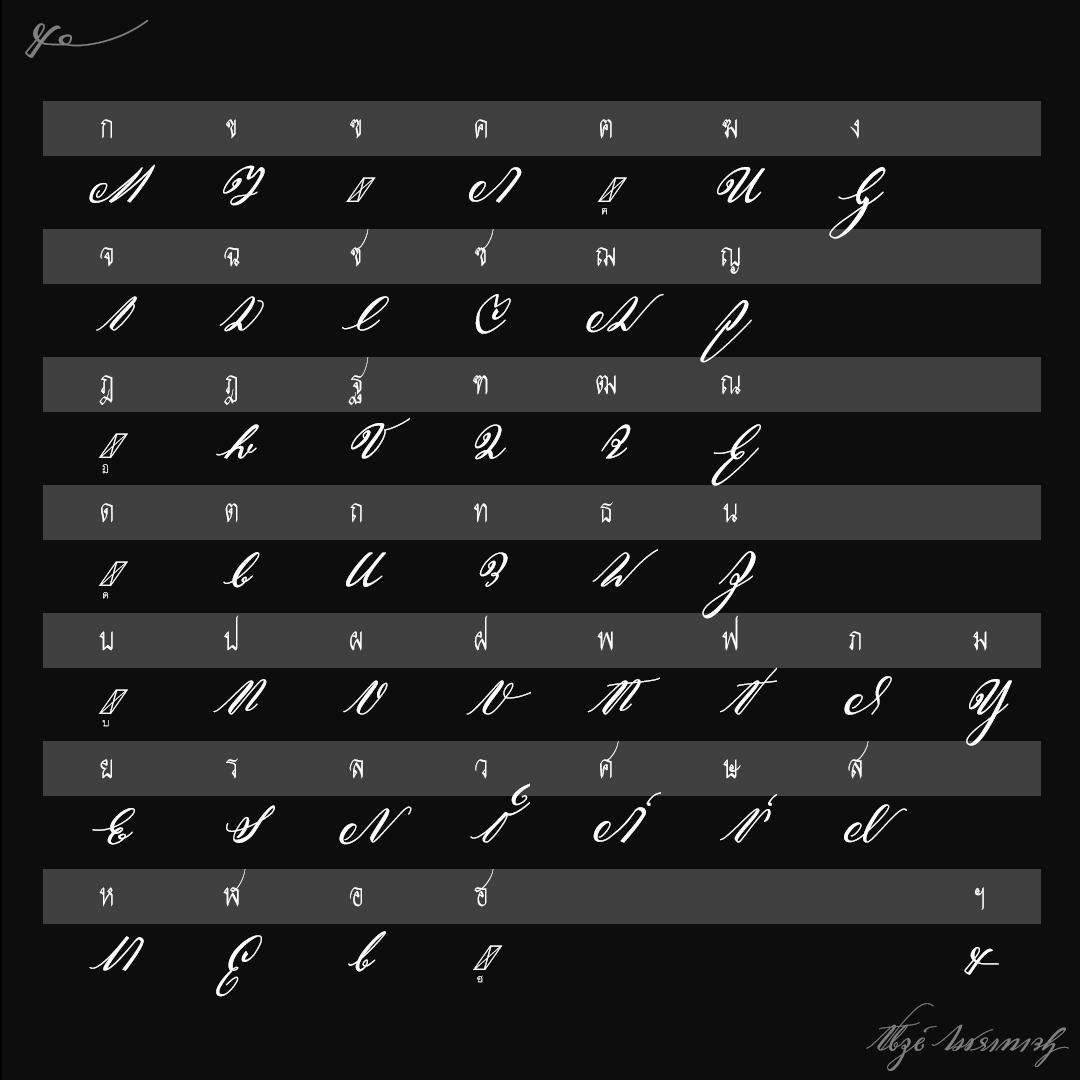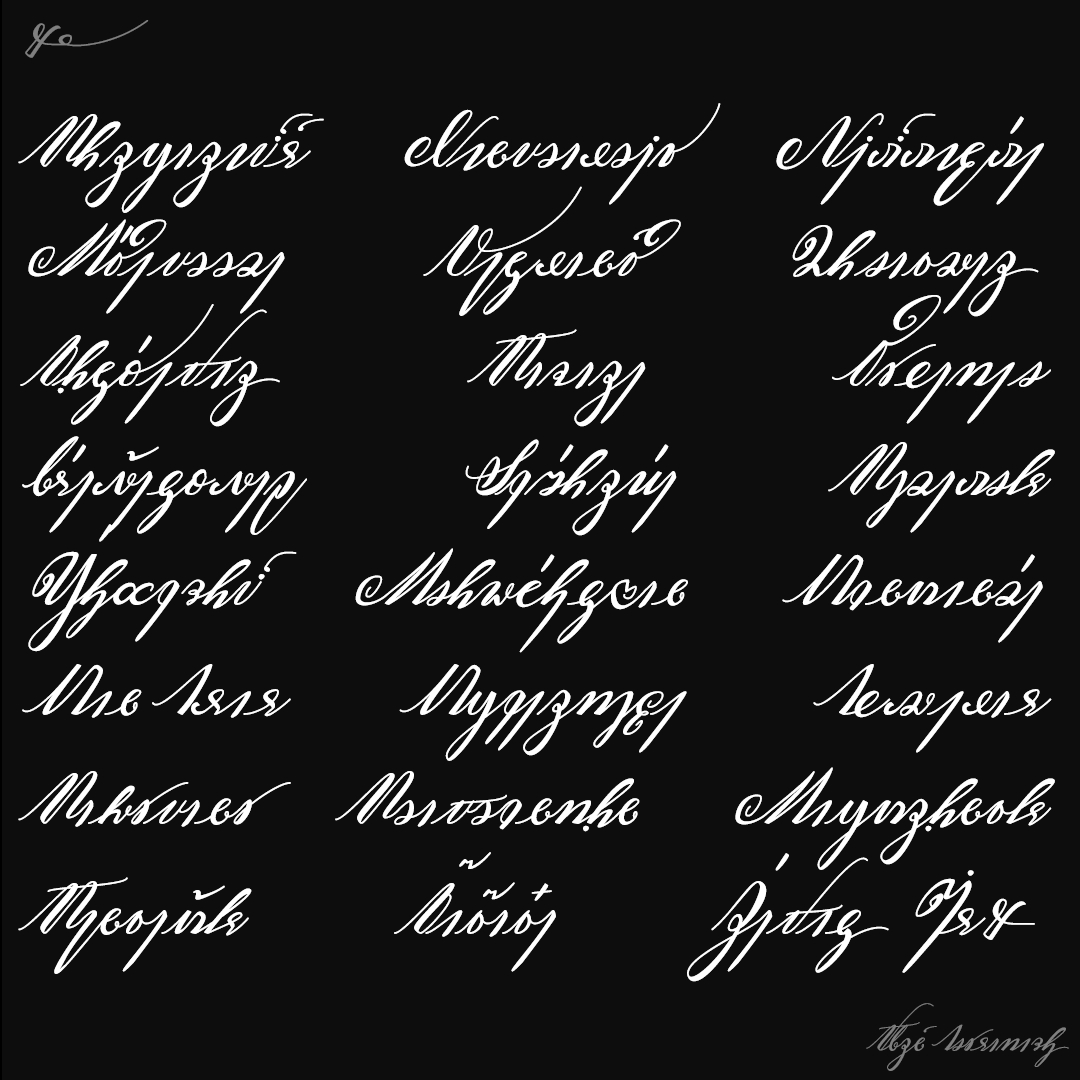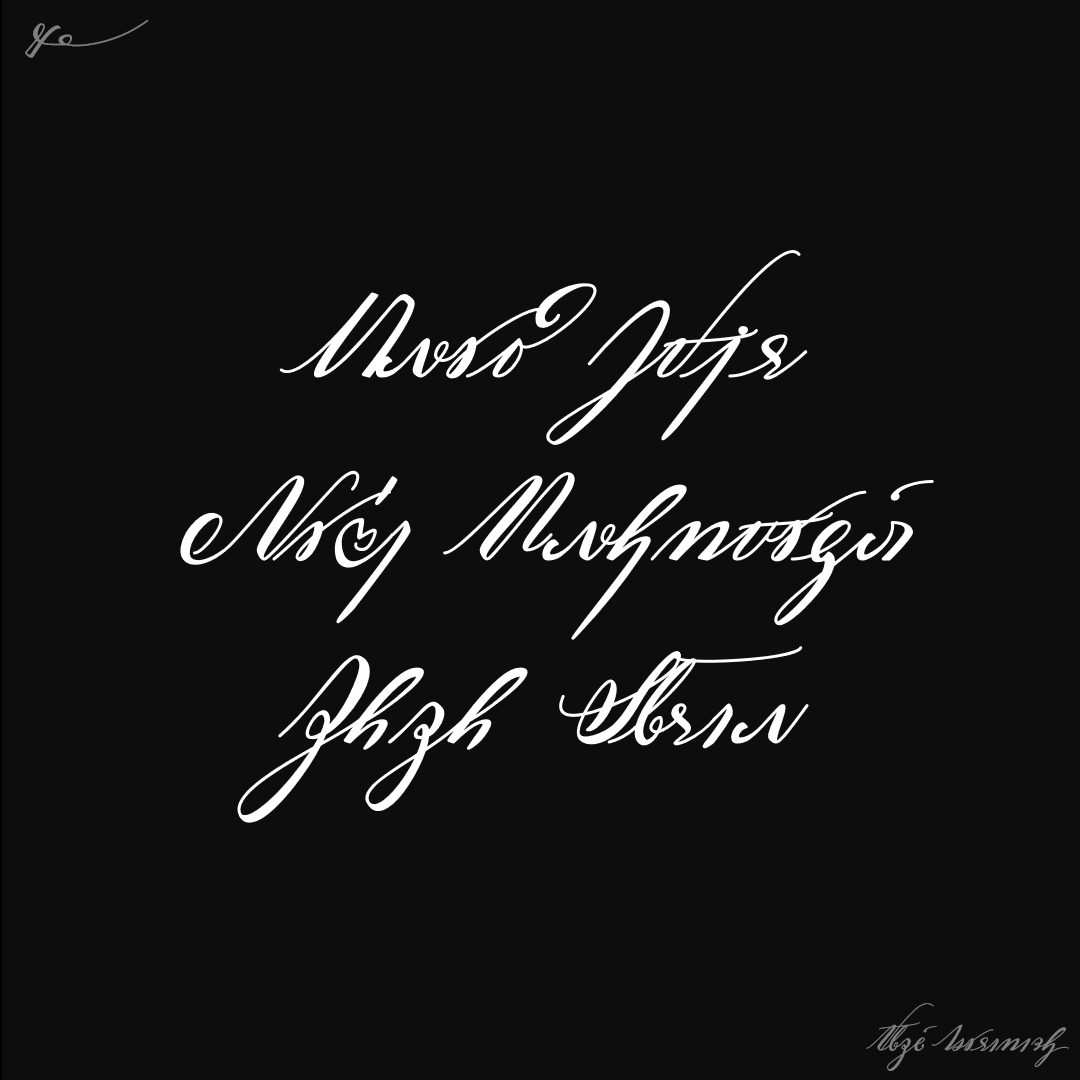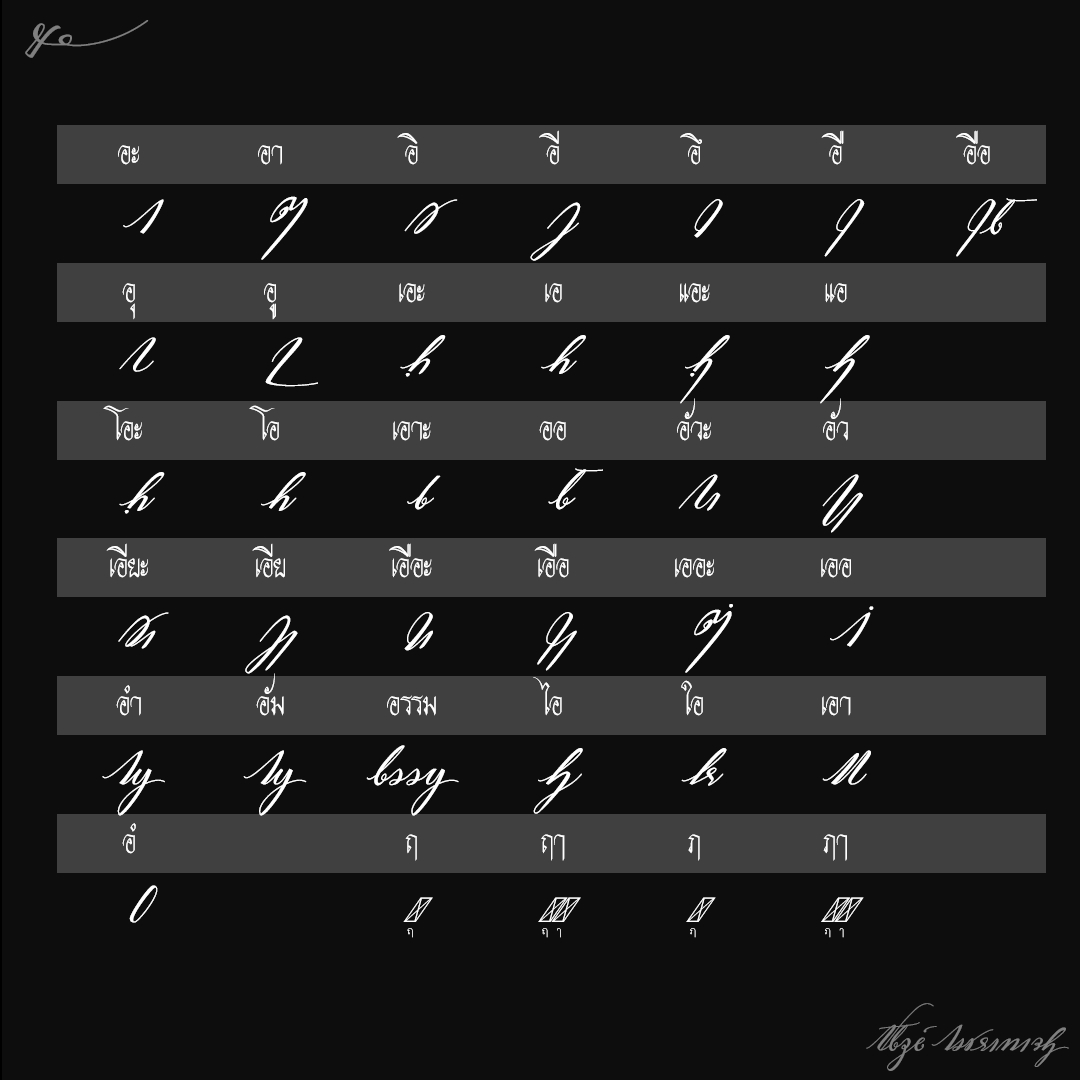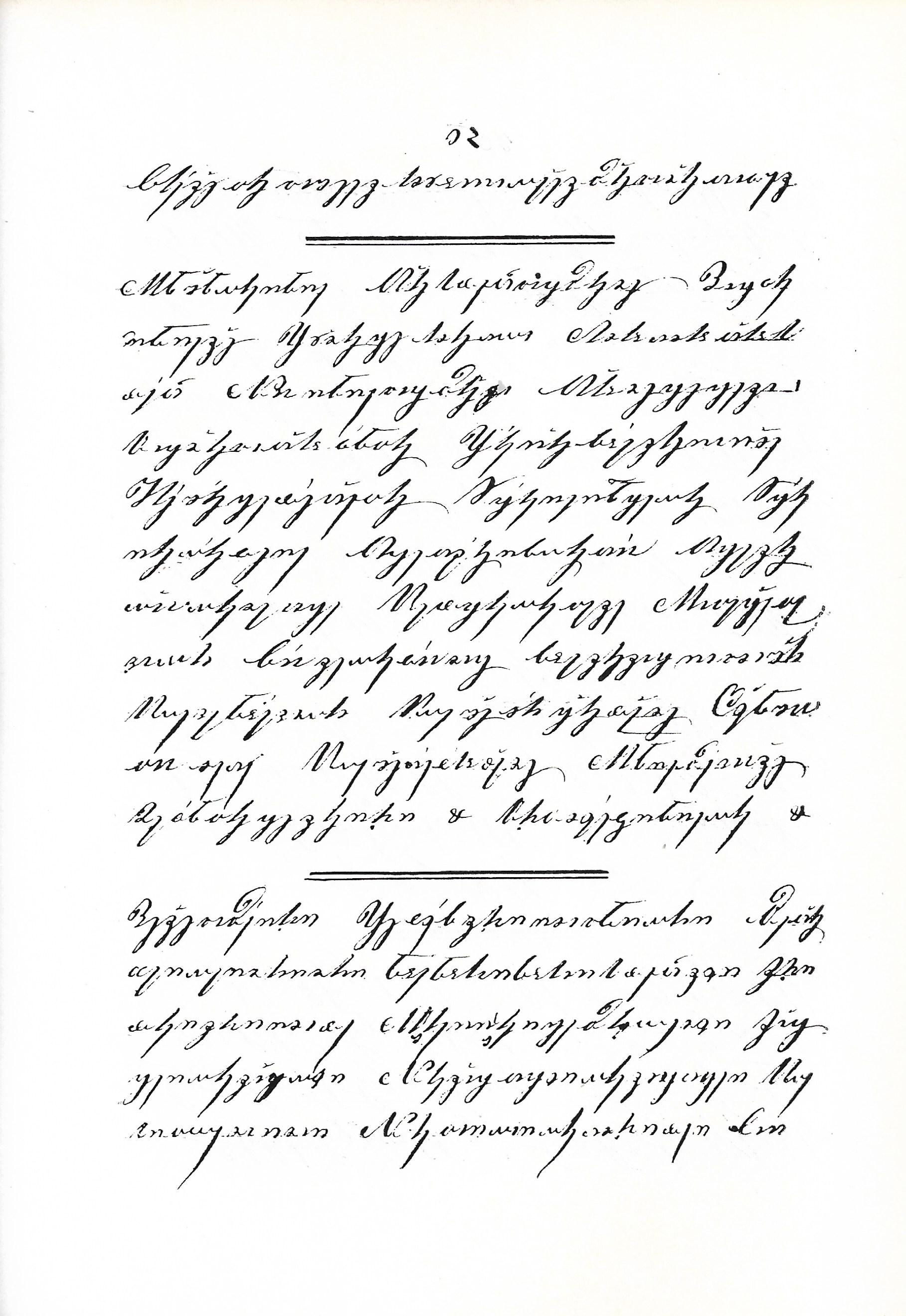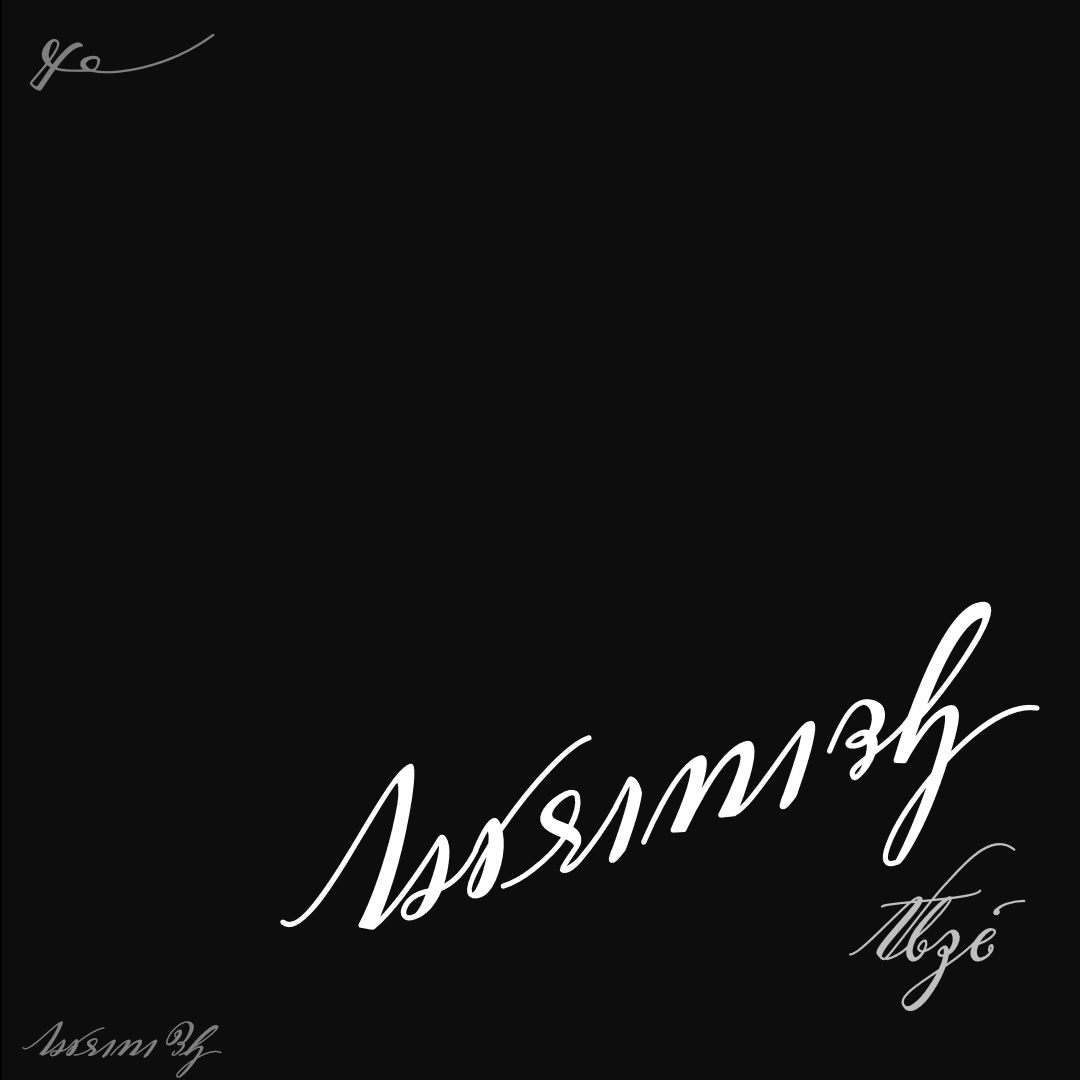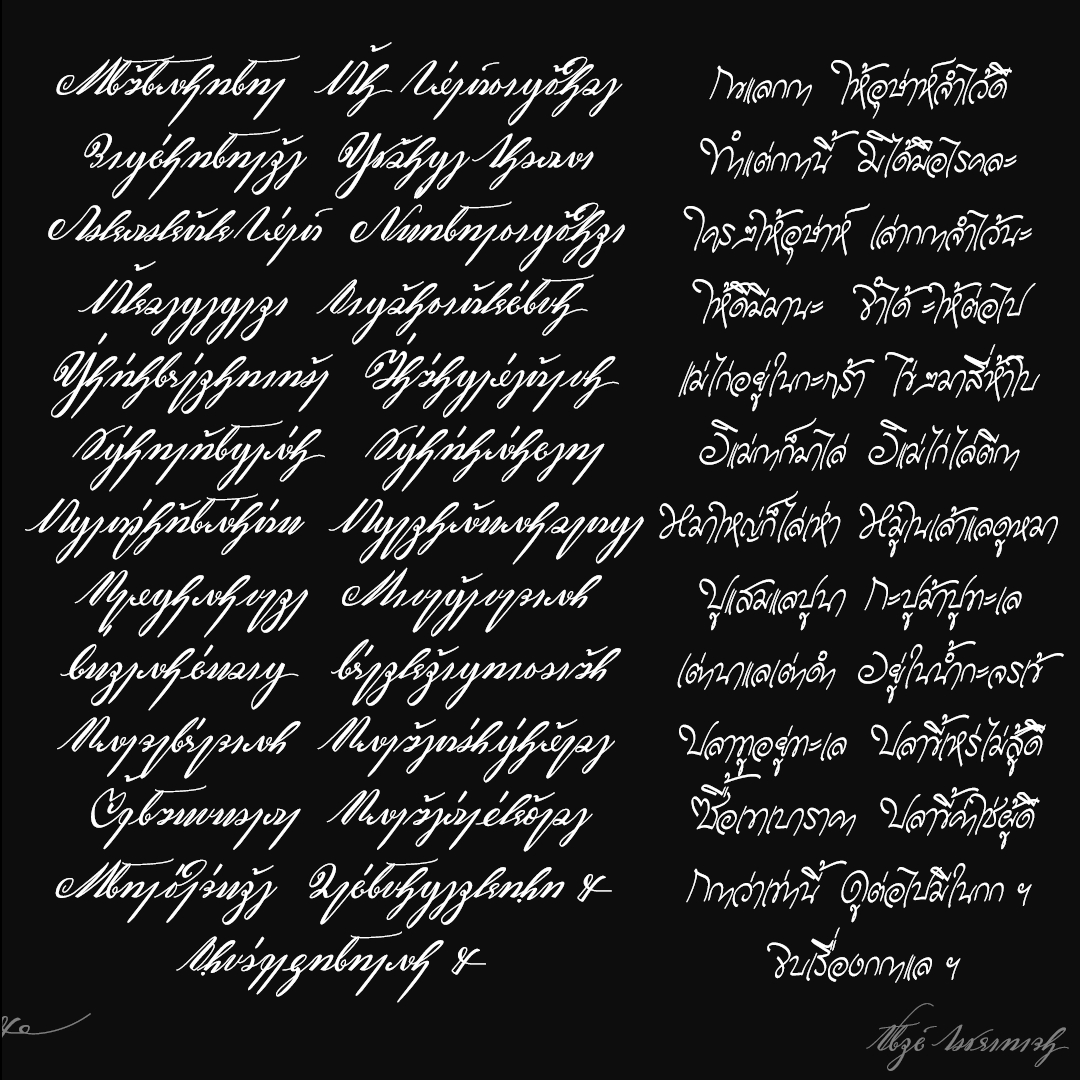
ฟอนต์ อริยกะไท
ฟอนต์อักษรอริยกะตัวเขียน ใช้ได้ทั้งภาษาไทย และภาษาบาลี ..ต่างจากอักษรปัจจุบันทั้งรูปอักษร วิธีพิมพ์ แนะนำให้ดูคู่มือก่อนใช้งาน
แต่เริ่มก็ไม่รู้ว่าใช้เขียนภาษาไทยได้ แต่พอเฉลย ประถม กกา ก็ไม่ต้องสงสัยอีก
แพนแกรม
นึกอุตริว่า ใช้เป็นลายเซ็น ก็ได้อยู่นะ
แถม.. ฟอนต์อริยกะปาฬิ(AriyakaPL) สำหรับบาลีตัวเขียนโดยเฉพาะ..พิมพ์แบบไทยพินทุ
เล่าเรื่องเบื้องหลัง
1. การมีต้นแบบอักษร นั้นทำให้เราเริ่มทำฟอนต์ได้ แต่ไม่สามารถจบงานได้จริง
2. จะจบงานได้ ต้องรู้ว่าใช้งานยังไง เขียนยังไง เว้นวรรคแค่ไหน ..แต่ได้มาแล้ว อ่านไม่ออกล่ะ จะทำยังไง???
3. งานนี้ ทำให้เข้าใจนักอ่านอักษรโบราณ ขึ้นเยอะ ว่าต้องมีองค์ความรู้เยอะๆ แล้วเชื่อมโยงกันให้ได้
การอ่านเนื้อความทั้งหมดอาจจะยาก แต่ถ้าแกะได้บางส่วน แล้วเอาองค์ความรู้อื่นมาประกอบ ก็อาจจะจบงานได้
เช่น ในรูปก่อนหน้า คือข้อความที่ตรงกับเอกสารนี้ .. พอรู้ปุ๊บ จากอ่านไม่ออก แกะอักษรไม่ได้ ก็อ่านออกทันทีเลย
หรือ คำแรกสุด ของรูปบน เขียนว่า สุภมัตถุ --> คือไรหว่า?  แต่ถ้าเคยอ่านเอกสารโบราณ ก็จะพบคำคล้ายๆนี้ขึ้นต้นเอกสารเสมอ "ศุภมัสดุ"
โชคดีที่ผมไปเจอ clip สัมนาที่มีการพูดเรื่องนี้ ทำให้รู้ว่าจะต้องหาเอกสารเล่มไหน และสามารถตรวจสอบความถูกต้องของฟอนต์ที่ทำได้ รวมถึงตัวอักษรที่ไม่มีรูปอักษร ว่าต้องใช้งานยังไง
..สนุกจัง